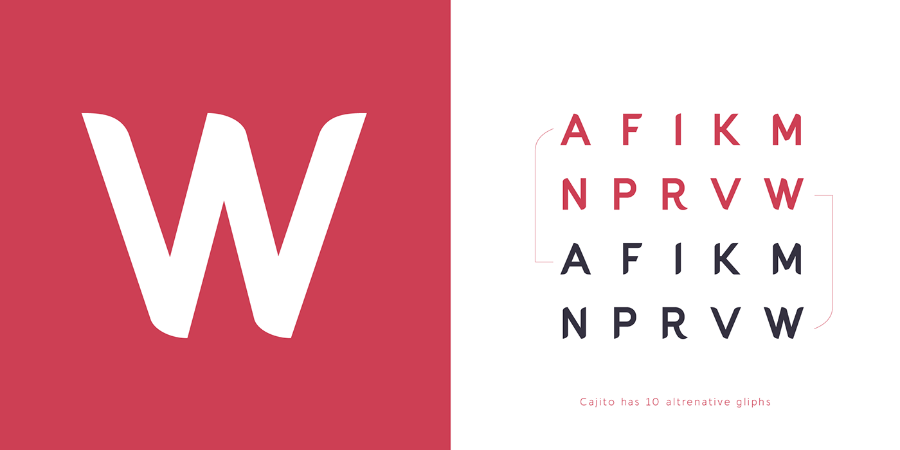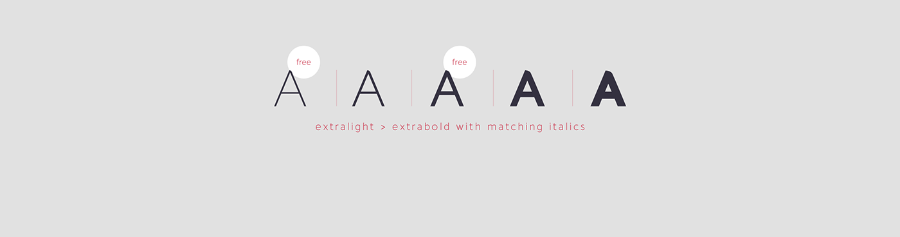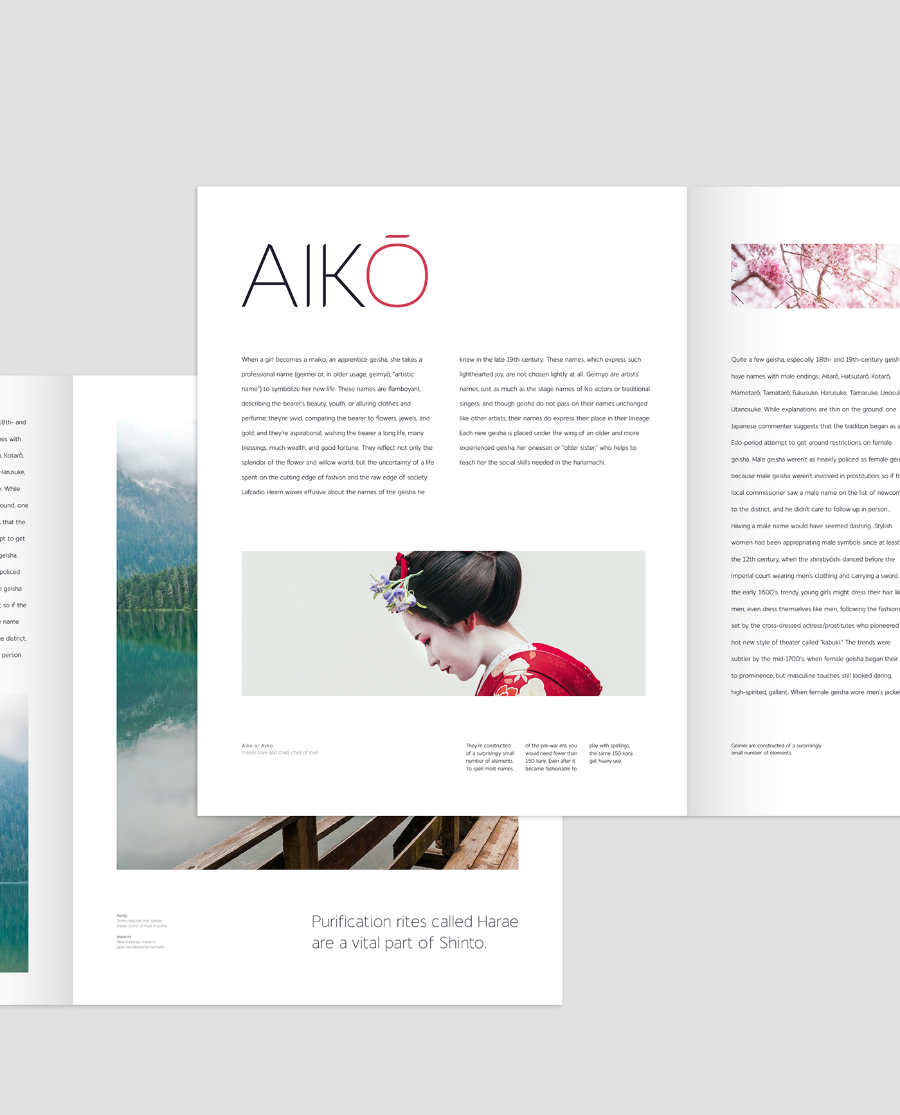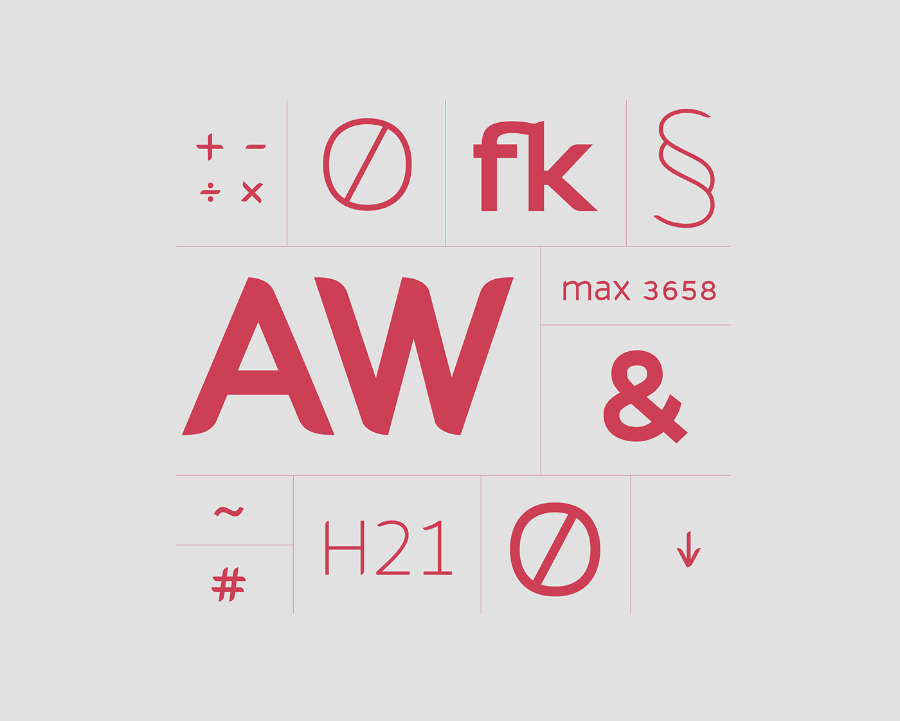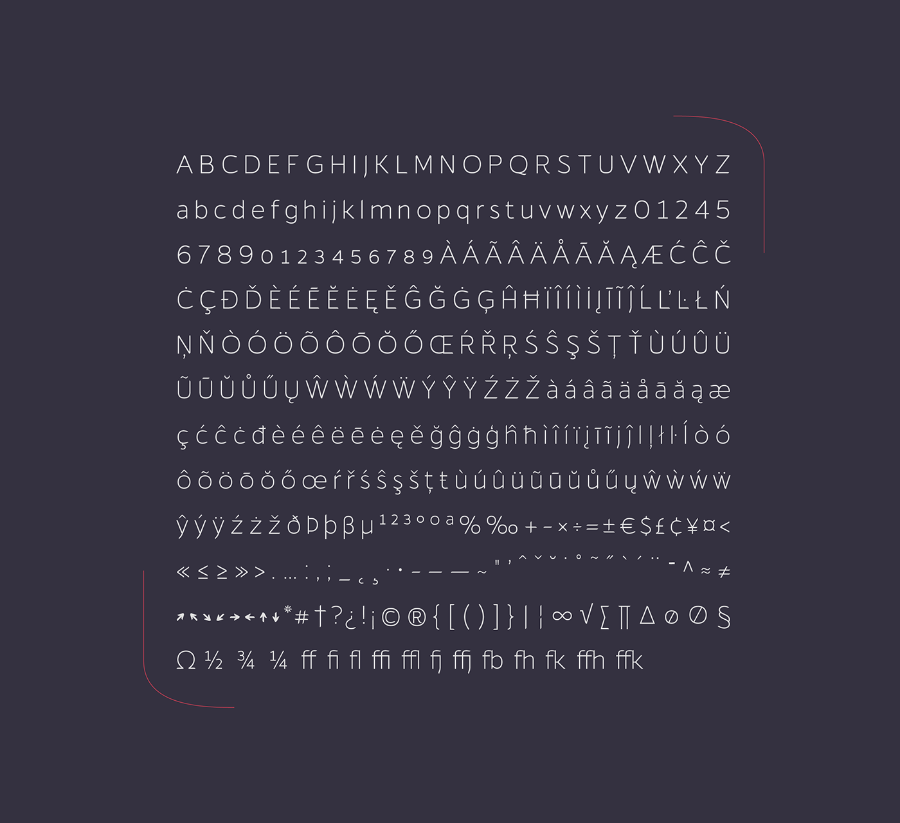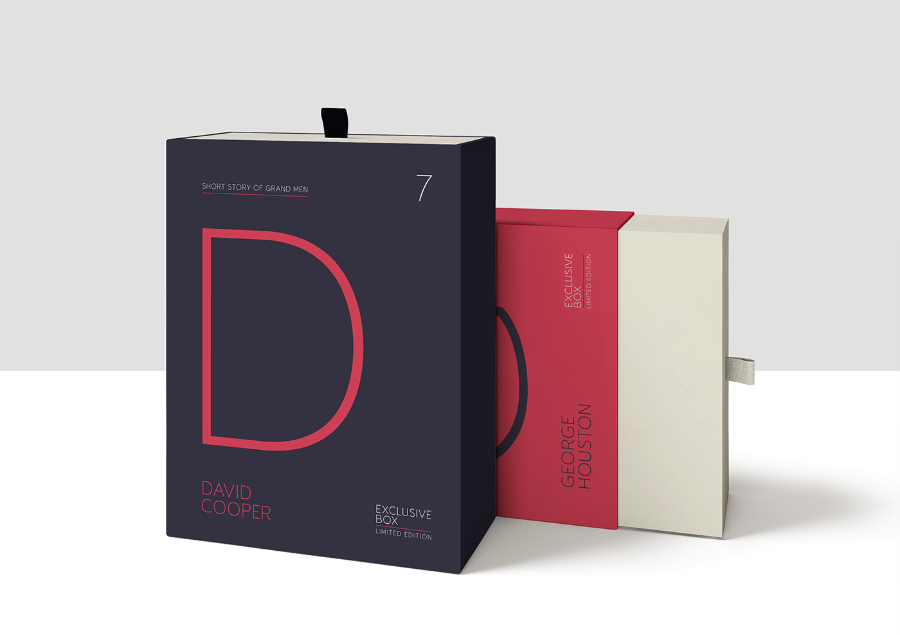
Cajito字体家庭免费演示
Cajito Font Family Free Demo
Cajito字体家庭免费演示是一个中等对比度的字体家族的一部分,开发用于多种用途。这个演示包包含Cajito定期和额外的光。您可以在移动应用程序,网站和目录中使用此系列,尤其是徽标设计的企业设计。 Cajito有十个可选的首都,他的终端看起来像鱼的鳍。这个家庭由五个权重从额外的光线,特别是粗体斜体匹配。